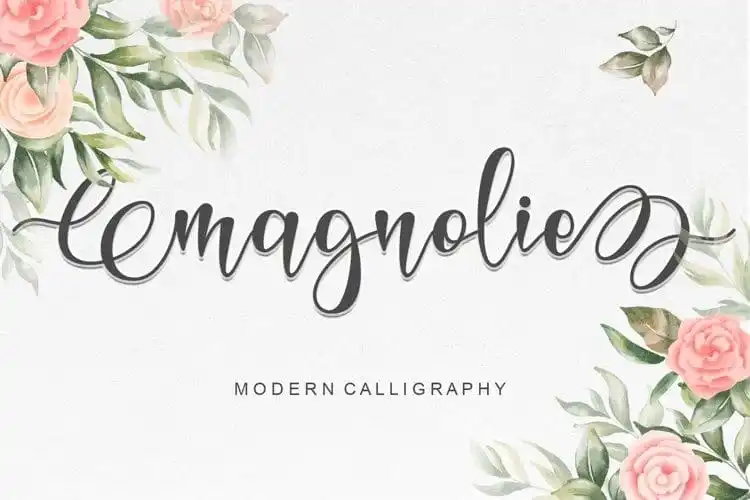
Magnolie Calligraphy Font é uma elegante tipografia feminina criada por Ahmad Afandi. Este tipo de letra apresenta swashes incrivelmente sofisticadas que adicionam uma delicadeza incomparável às suas criações. As letras ondulantes proporcionam um visual único e suave, tornando-o perfeito para um vasto range de projetos, incluindo logomarcas, cartões de agradecimento, embalagens, identidades de marca, projetos DIY, títulos de livros, convites de casamento e embalagens. Esta fonte é uma escolha ideal para quem busca uma pitada feminina em seus designs sem comprometer a modernidade e sofisticação do design gráfico atual.